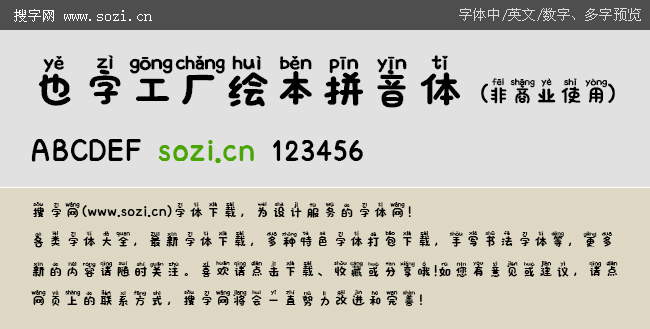
也字工廠繪本拼音體
搜字網(wǎng)給大家提供一款也字工廠繪本拼音體(非商業(yè)使用)中文字體下載,也字工廠繪本拼音體是一款卡通字體,字體書寫可愛(ài)有趣,充滿童真,字體還配有漢語(yǔ)拼音。具有很好的視覺(jué)效果。適合應(yīng)用于兒童繪本、兒童海報(bào)、網(wǎng)頁(yè)設(shè)計(jì)等應(yīng)用(此字體為個(gè)人非商用版,商用可以聯(lián)系:官方網(wǎng)址:https://yefont.com/home,聯(lián)系方式:13798980448)。